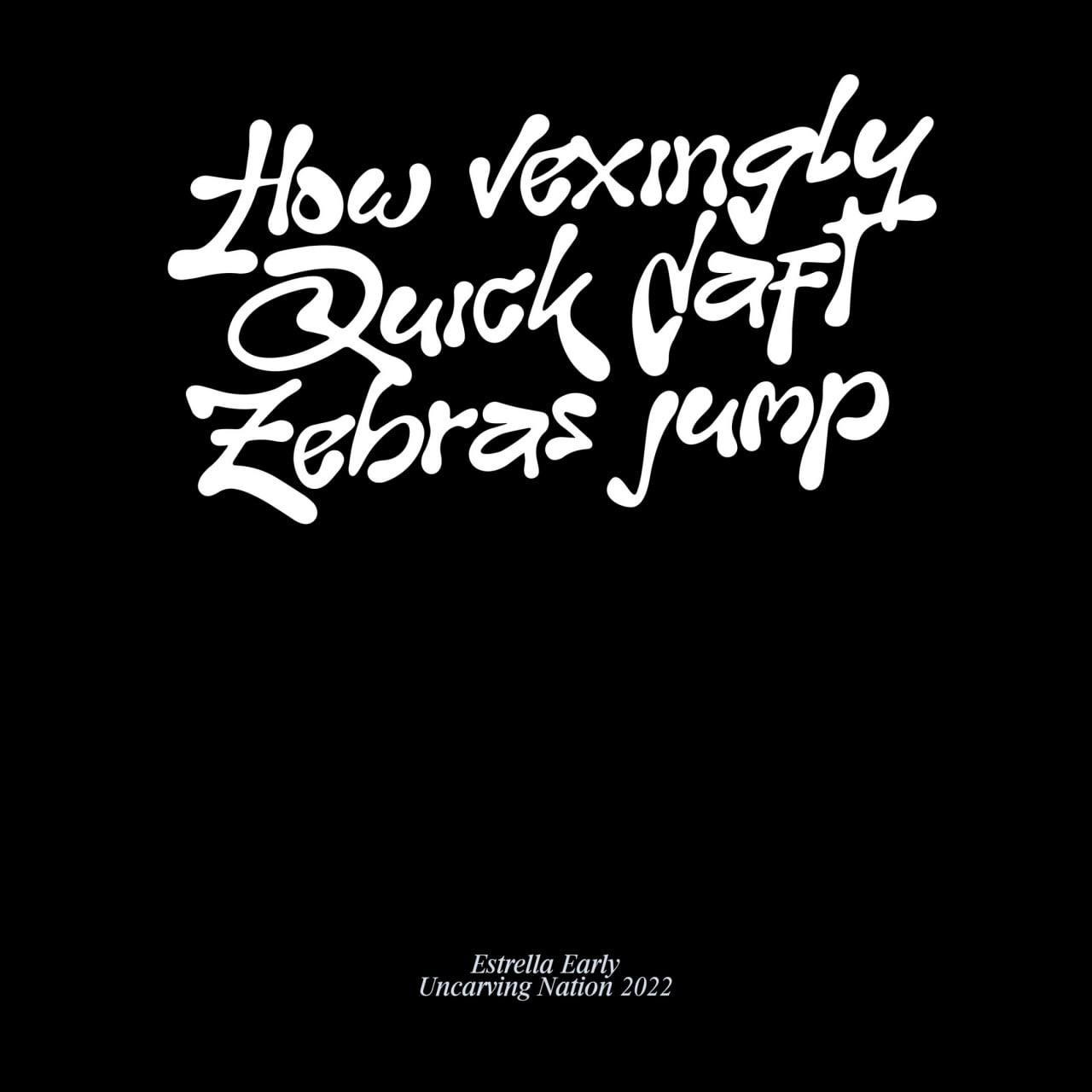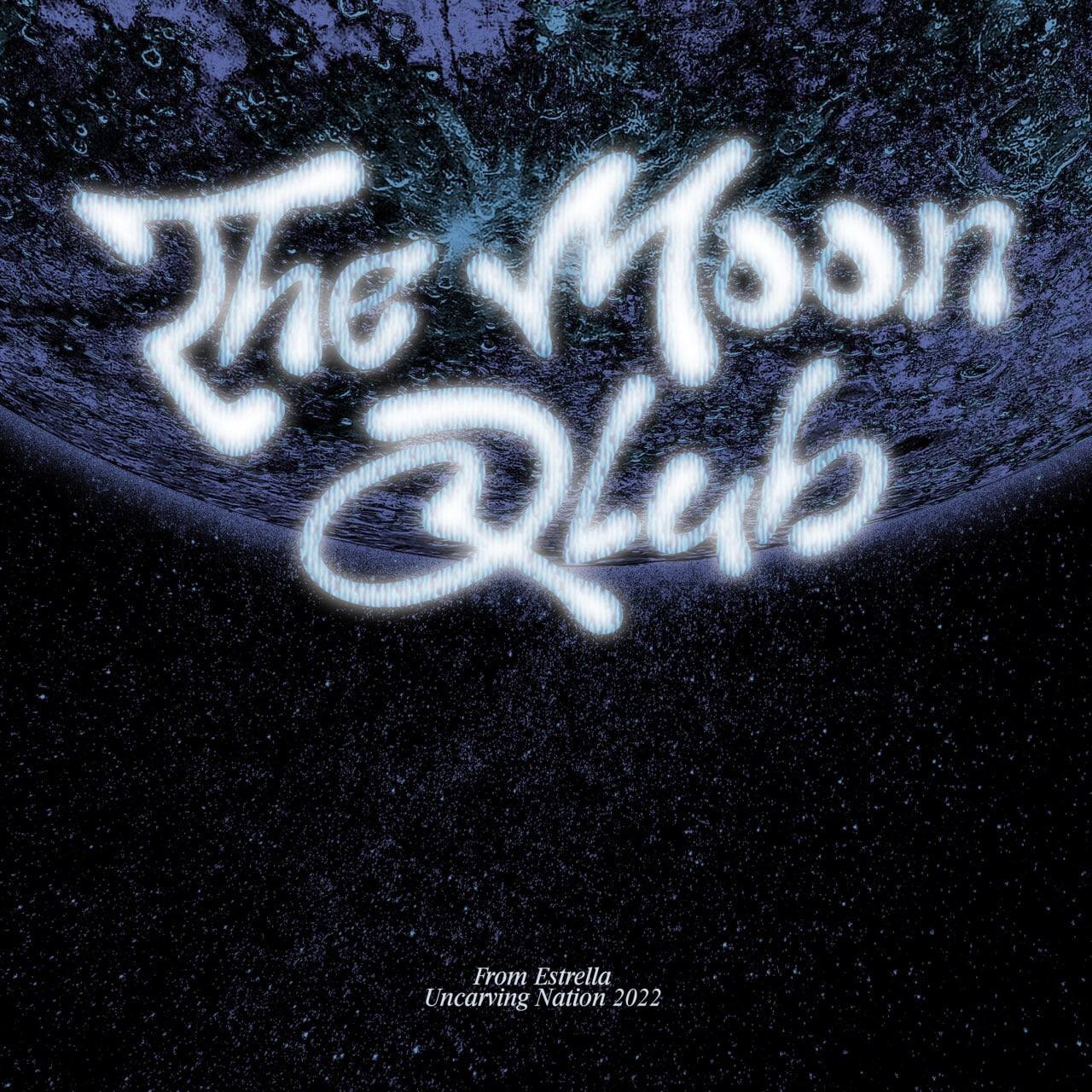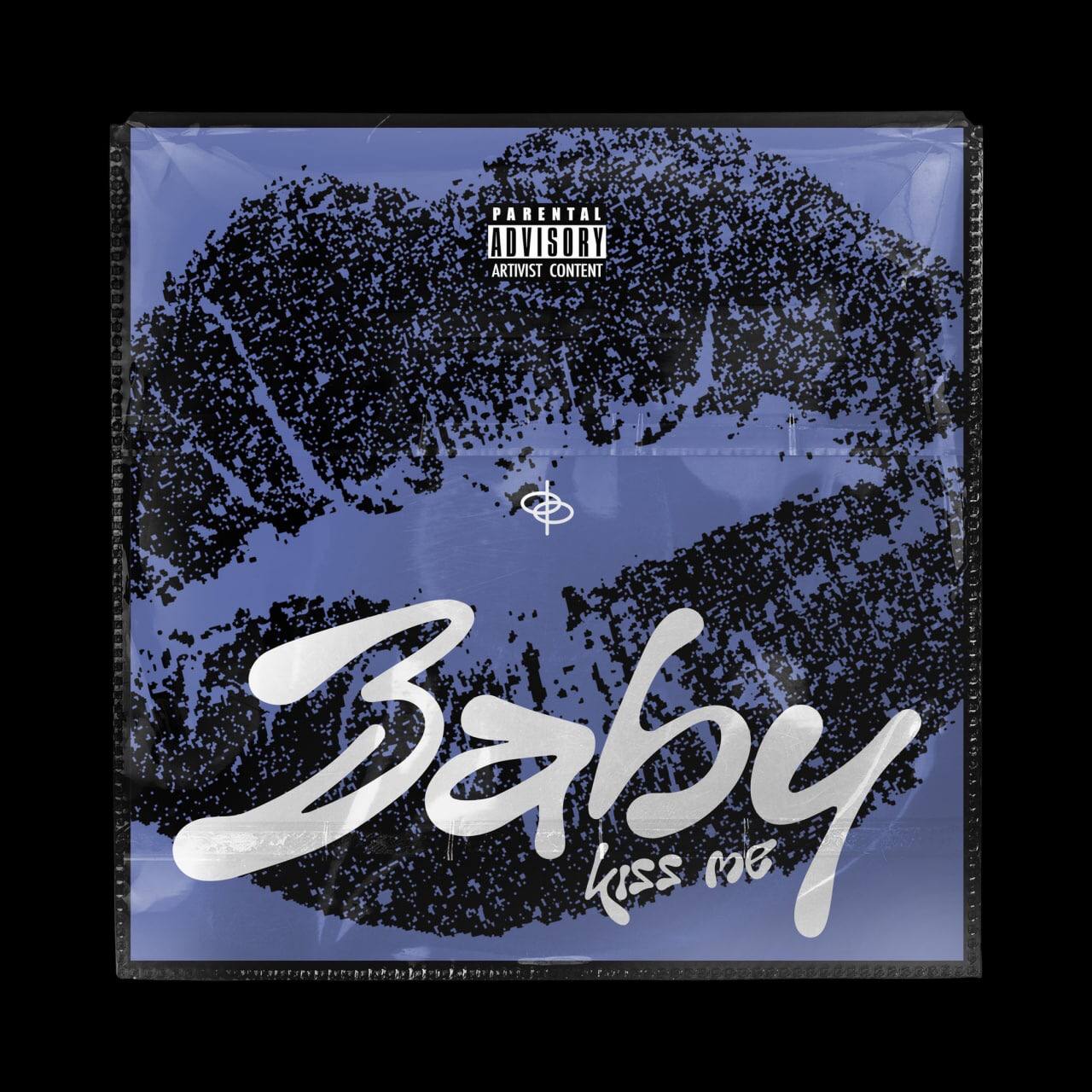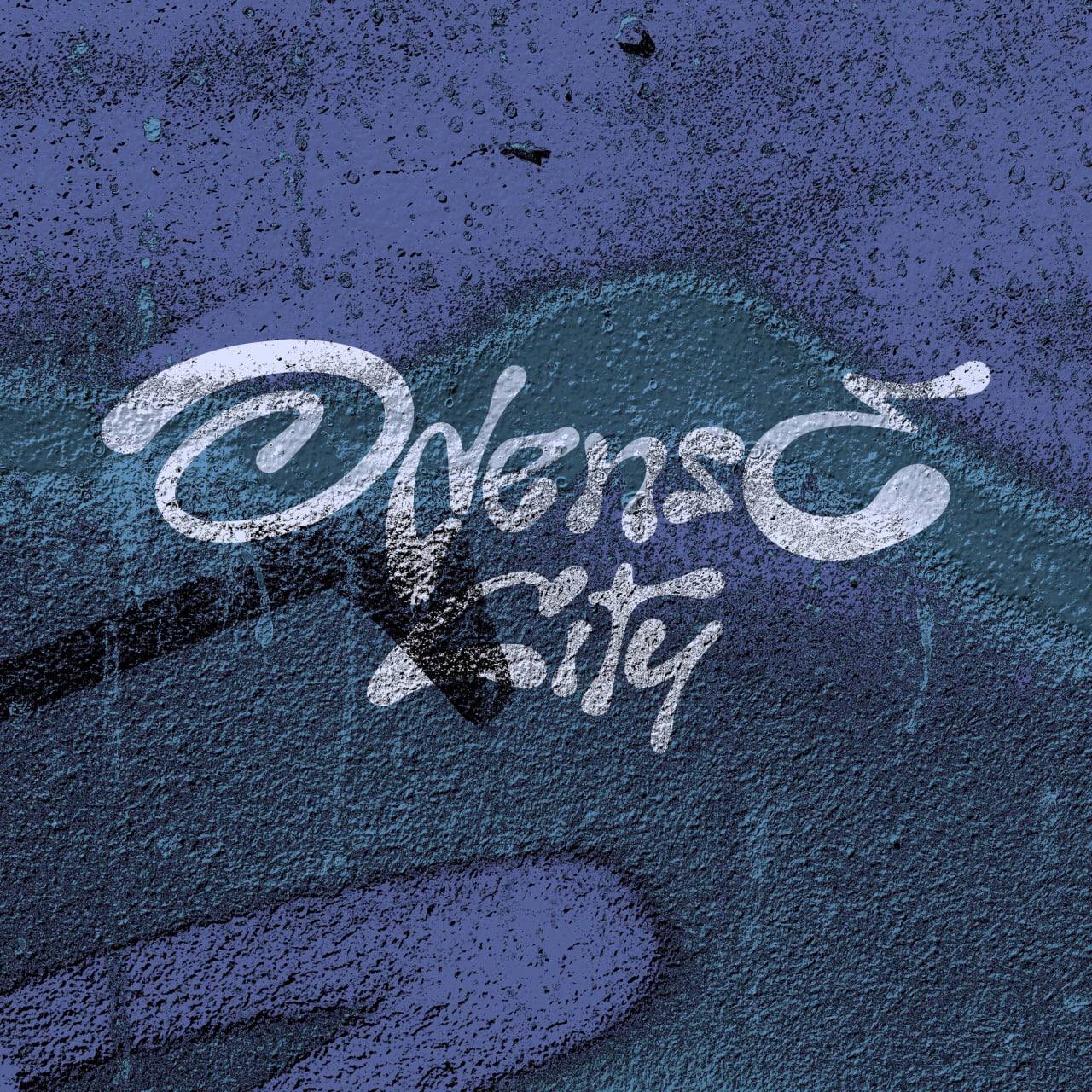
Estrella Typeface có phông chữ hiển thị với những đường cong biểu cảm nên trông vui tươi và vui nhộn. Kiểu này được lấy cảm hứng từ các kiểu chữ của thập niên 70 với những nét ảo giác và cảm giác hấp dẫn. Estrella là phông chữ hiển thị miễn phí mới được thiết kế bởi Uncarving Nation. Phông chữ dạng tự do thử nghiệm này rất phù hợp cho các dự án xây dựng thương hiệu, áp phích, tiêu đề và hơn thế nữa!